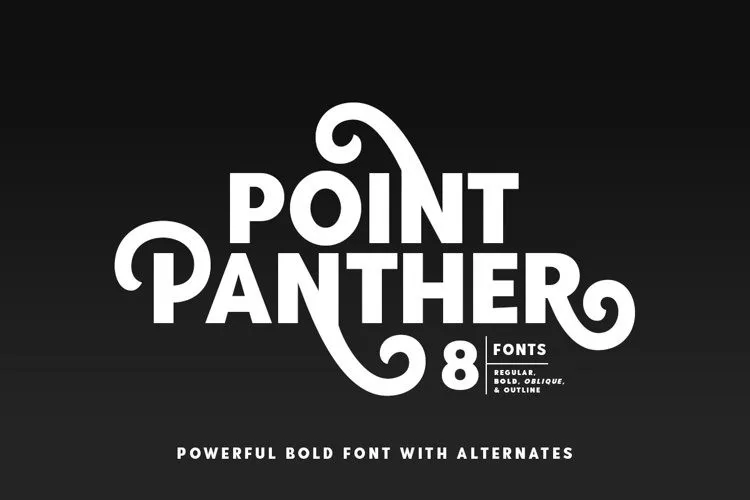
A fonte Point Panther é uma tipografia sans-serif criada para oferecer um visual moderno e fresco. Ideal para empresas que querem se destacar com um visual único, essa família de fontes inclui estilos bold e itálico, dando-lhe mais opções de design. Esta é uma ótima escolha para criação de marcas, artesanato, artefatos publicitários ou até mesmo a arte na rua, garantindo que sua identidade visual seja reconhecível e moderna. Com suporte para múltiplas línguas, essa fonte está pronta para expandir seu alcance global. É perfeita para aqueles que buscam uma maneira de dar um gás novo ao seu trabalho gráfico sem comprometer o design elegante ou sofisticado da fonte Point Panther.